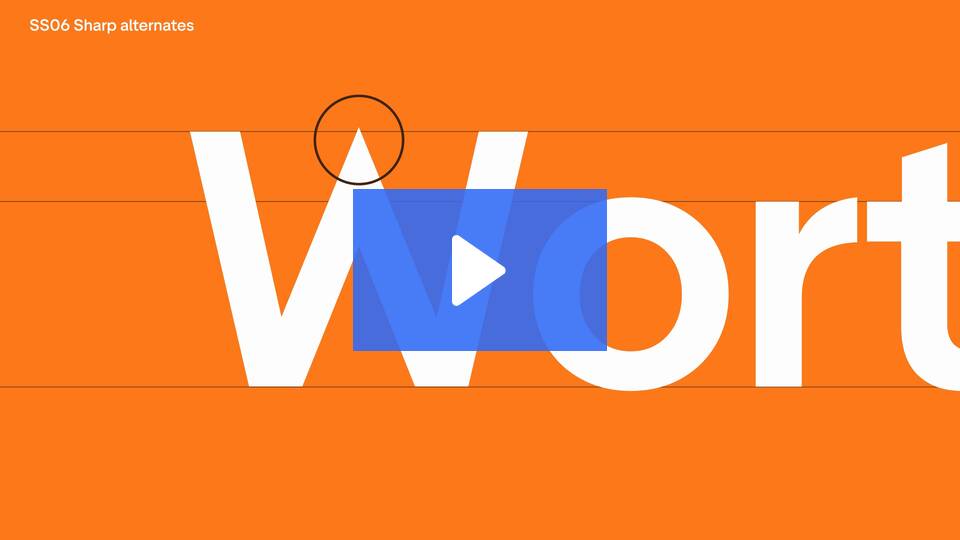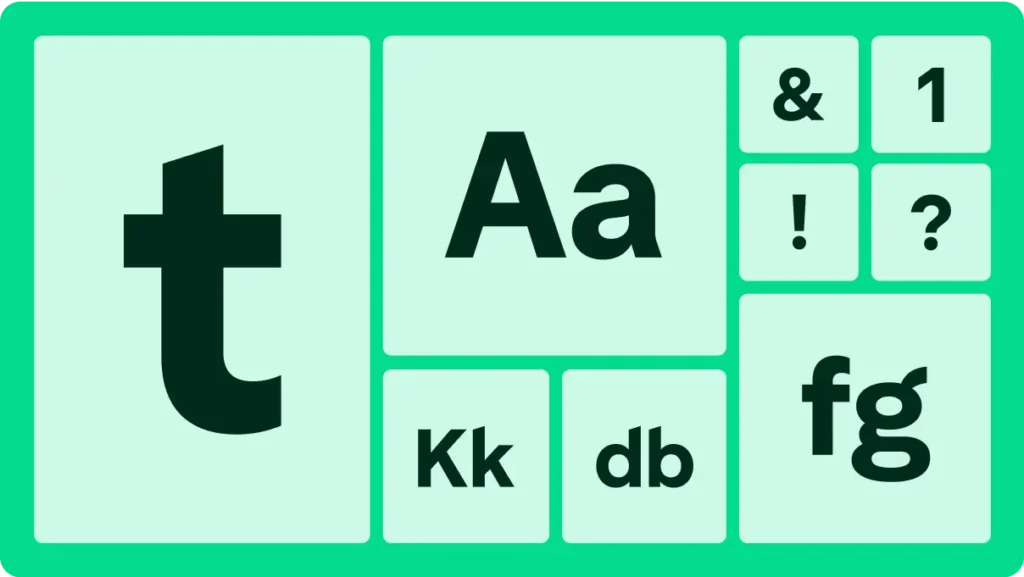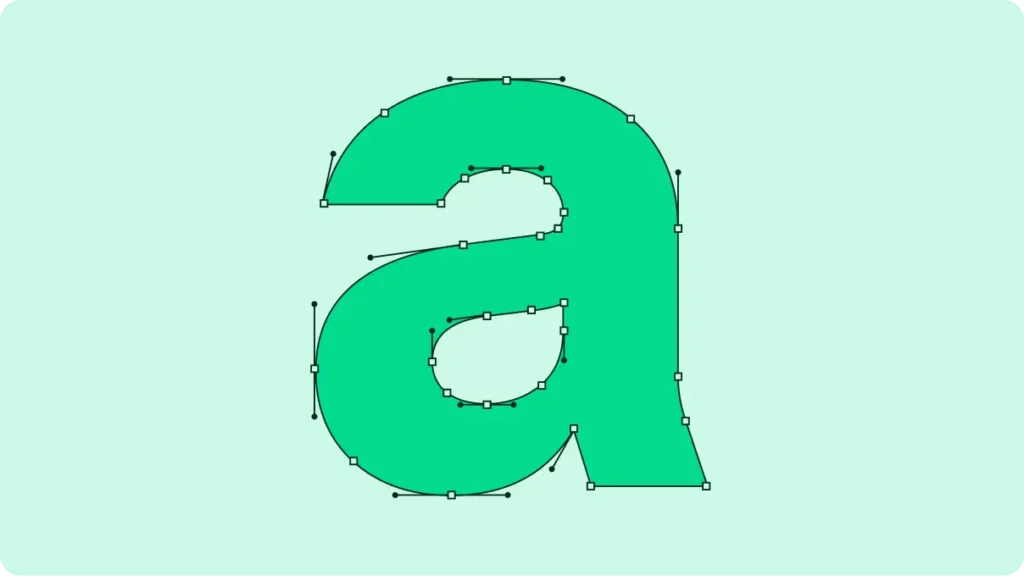
La plataforma global de reseñas online lanza una fuente tipográfica exclusiva desarrollada junto a Playtype para reforzar su identidad visual y transmitir sus valores de claridad y confianza.
Trustpilot, conocida por ser un espacio donde millones de consumidores comparten experiencias y las empresas interactúan para mejorar su reputación, ha dado un nuevo paso en su estrategia de diseño. La compañía acaba de anunciar el lanzamiento de Trustpilot Sans, una tipografía creada en colaboración con el estudio danés Playtype, que a partir de hoy comenzará a implementarse en su web, aplicación y materiales de comunicación.
El vicepresidente de diseño de Trustpilot, MC Dean, explica que la nueva tipografía “es un reflejo literal de nuestros valores fundamentales”. Se trata de una fuente variable sans serif que busca equilibrar la legibilidad, la claridad y la cercanía, tres conceptos que la empresa identifica con su compromiso de fomentar interacciones transparentes y honestas entre usuarios y marcas.
Dean detalla que en su construcción se han incorporado elementos de la identidad visual de Trustpilot, como las aristas de la estrella que simboliza sus valoraciones. El resultado es una tipografía que combina rasgos clásicos y contemporáneos, con líneas limpias y curvas suaves, diseñada para transmitir fiabilidad y accesibilidad.
La tipografía no solo es un ejercicio estético, sino también una herramienta estratégica para fortalecer la comunicación. Según Alex Smith, director creativo sénior en Trustpilot, el nuevo diseño “mejora la claridad, potencia la accesibilidad y refuerza la identidad visual de la marca, permitiéndonos comunicar con mayor calidez, precisión y coherencia”.
Smith subraya que Trustpilot Sans “captura la energía y diversidad de nuestra audiencia global” y que se concibe como una manera más humana y atractiva de contar la historia de la plataforma. La tipografía estará presente no solo en los entornos digitales, sino también en acciones de marketing, eventos y cualquier espacio donde la marca tenga visibilidad.
El lanzamiento de Trustpilot Sans responde a una tendencia cada vez más extendida: las grandes plataformas digitales apuestan por tipografías propias que refuercen su singularidad y aporten consistencia a sus productos y servicios. En este caso, la apuesta se asocia directamente a la misión de la empresa de promover la transparencia y la confianza como valores diferenciales en la relación entre consumidores y compañías.
La implementación de la nueva tipografía ya ha comenzado en el blog corporativo y se desplegará progresivamente en todas las interfaces de Trustpilot en las próximas semanas.